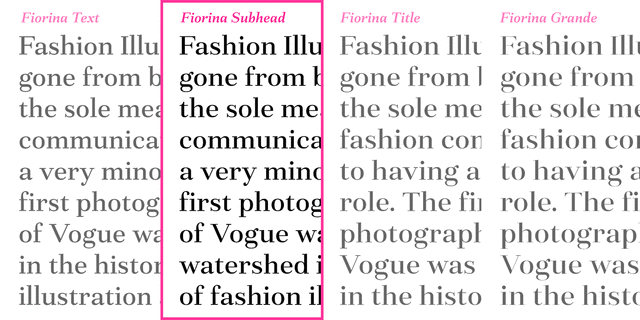
Версия шрифта для подзаголовков. Fiorina – это антиква нового стиля, состоящая из 72 начертаний. Шрифт поставляется в 4 оптических размерах: от текстового с умеренным контрастом до суперконтрастного Grande. Каждый из 4 наборов имеет 9 весов с соответствующим изысканным курсивом. Общее разнообразие начертаний делает Fiorina идеальной гарнитурой для журналов. Набор глифов поддерживает все европейские языки на основе латиницы, а также все основные языки, в которых используется кириллица. Шрифтовое семейство также поддерживает многочисленные функции OpenType, включая 6 наборов цифр, капитель, дроби, надстрочные и подстрочные индексы, порядковые числа и многое другое. Шрифт разработал Андрей Константинов в студии Mint Type в 2020 году.
Строгий, ровный, гармоничный, техничный, современный, культурный, образованный, устойчивый, серьезный, солидный, эффектный, модный, качественный, элитный, дорогой, богатый, городской, резкий, четкий, динамичный, роскошный, отборный, чистый, утонченный, прохладный, свежий, благородный, красивый, элегантный, ювелирный, мастерский, эстетичный, изящный, художественный, знаменитый, драгоценный, комильфо, романтичный, гламурный, вежливый, изысканный